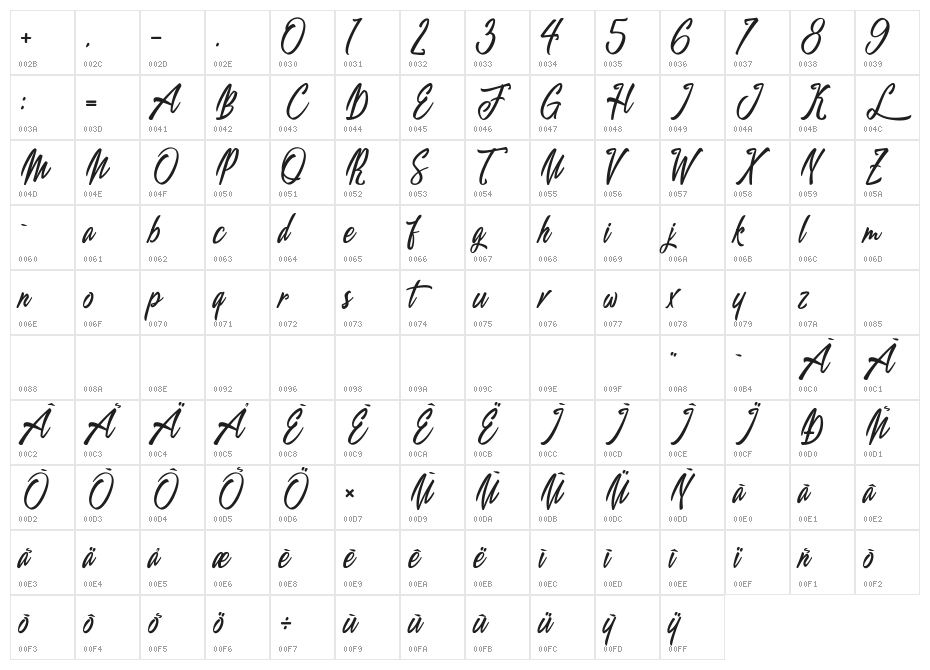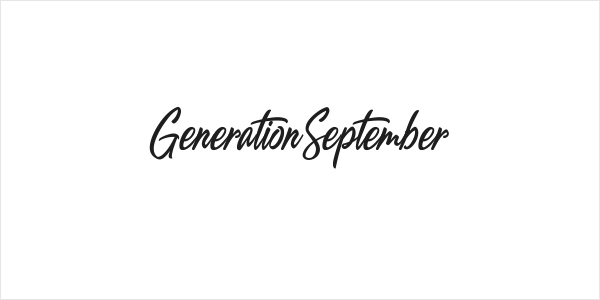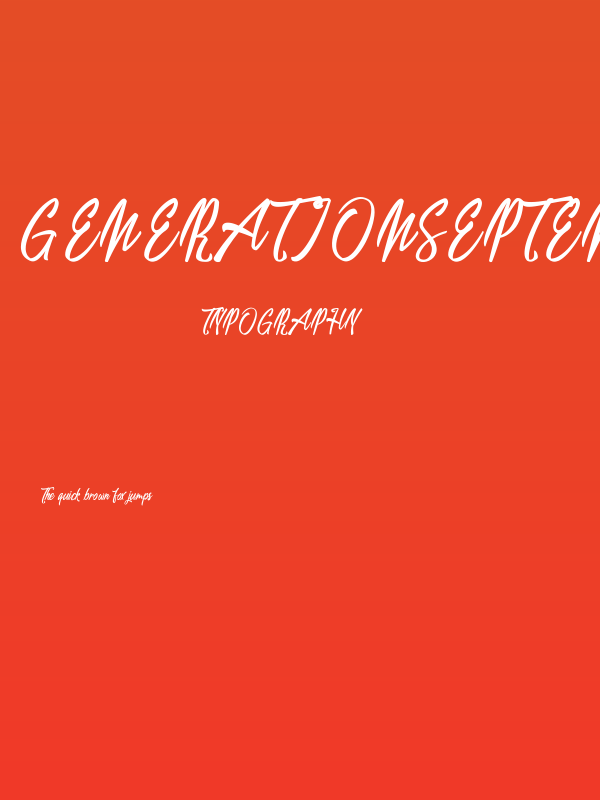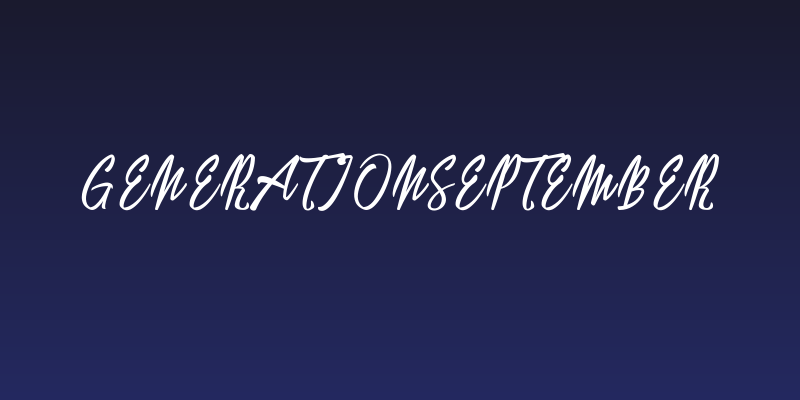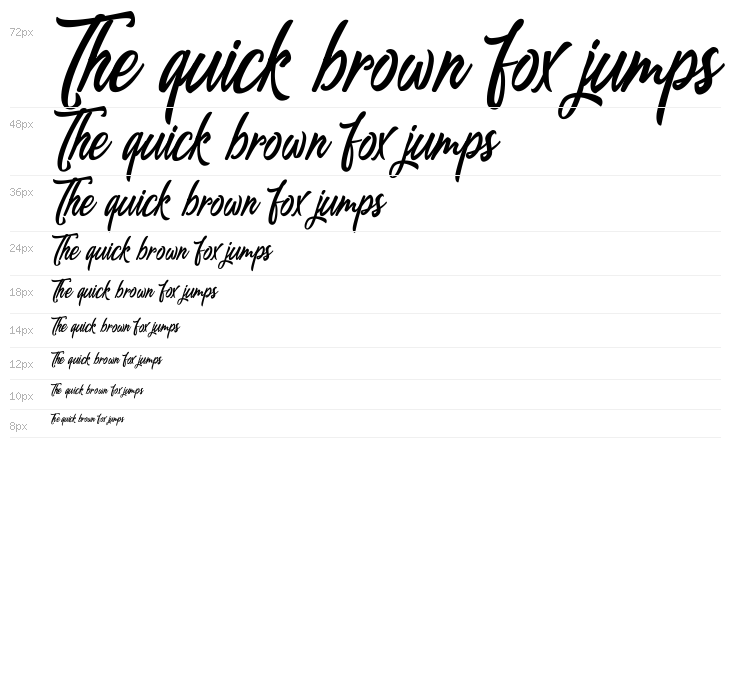
GenerationSeptember Font
✎ Script
| Caso de uso | Logos, Invitations, Artistic projects |
| Projetos propostos | Ideal for wedding invitations, branding, greeting cards, and artistic projects. |